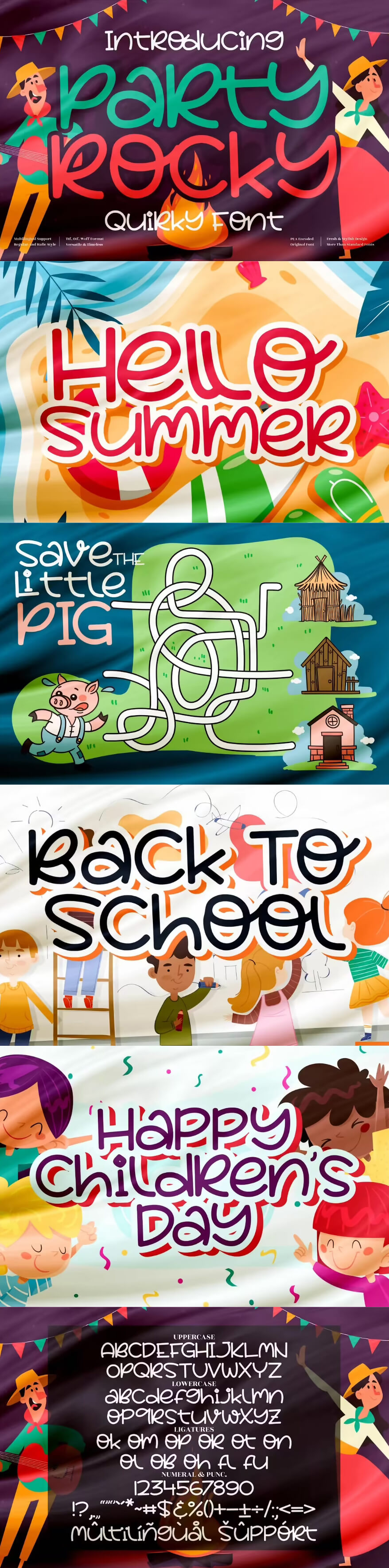
Шрифт - Party Rocky (Латиница)
Party Rocky - это необычный рукописный шрифт, подходящий почти для любых проектов. Это могут быть логотипы, упаковка, цитаты, плакаты на мероприятия, дизайн обложек детских книг и ещё много других проектов.
Шрифт - Party Rocky (Латиница)